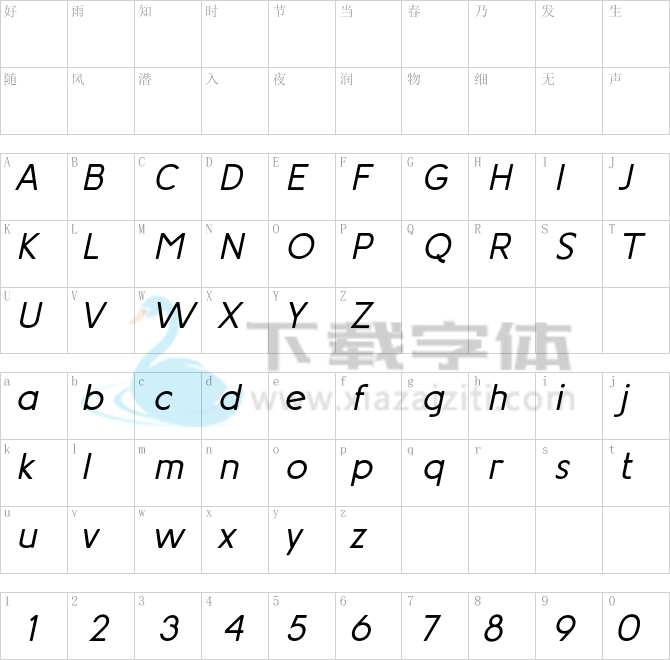
Aotani Medium Italic.otf字体下载,这款字体结构工整、笔画清晰,兼顾美观与易读性,适用于标题、正文、海报、包装、LOGO 等多种场景。字形优雅稳定,风格百搭耐看,适配日常排版与创意设计,让文字呈现更舒适、更具质感。Aotani Medium Italic.otf字体下载一笔一画,皆是细节,以均衡的比例、流畅的线条打造舒适视觉体验,字形端正大气,风格简约现代。无论是商业设计、品牌宣传还是日常排版,都能轻松驾驭,让文字更有格调与力量。Aotani Medium Italic.otf字体下载字体下载。